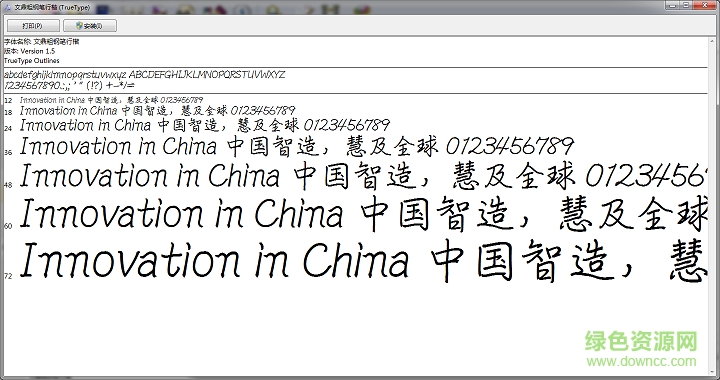
文鼎大鋼筆行楷是一款非常漂亮的鋼筆行楷字體,這款字體筆鋒細(xì)膩,筆畫行云流水,整體效果非常出色,喜歡這款字體的朋友可以來綠色資源網(wǎng)免費下載體驗!
文鼎大鋼筆行楷ttf是一款字形優(yōu)美的鋼筆字形,這款字體增強書寫映帶、表現(xiàn)書寫意趣以適當(dāng)加快書寫速度的,少量改變書寫筆順,且具較強易識、易學(xué)特征的實用性手寫體字體。